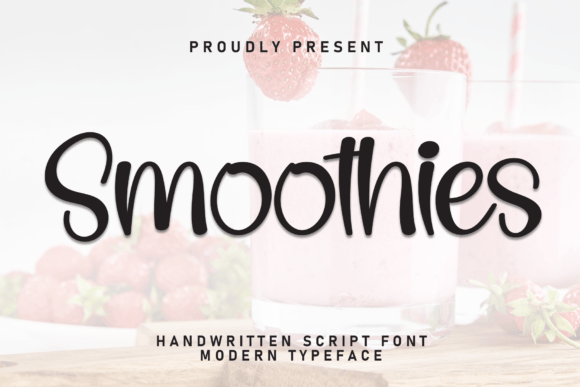
Smoothies
Si buscas recursos de alta calidad como Smoothies, este paquete premium es una opción fantástica para tus proyectos creativos.
Ya sea que estés creando productos POD (impresión bajo demanda), invitaciones de boda o gráficos para redes sociales, Smoothies es una opción ideal.